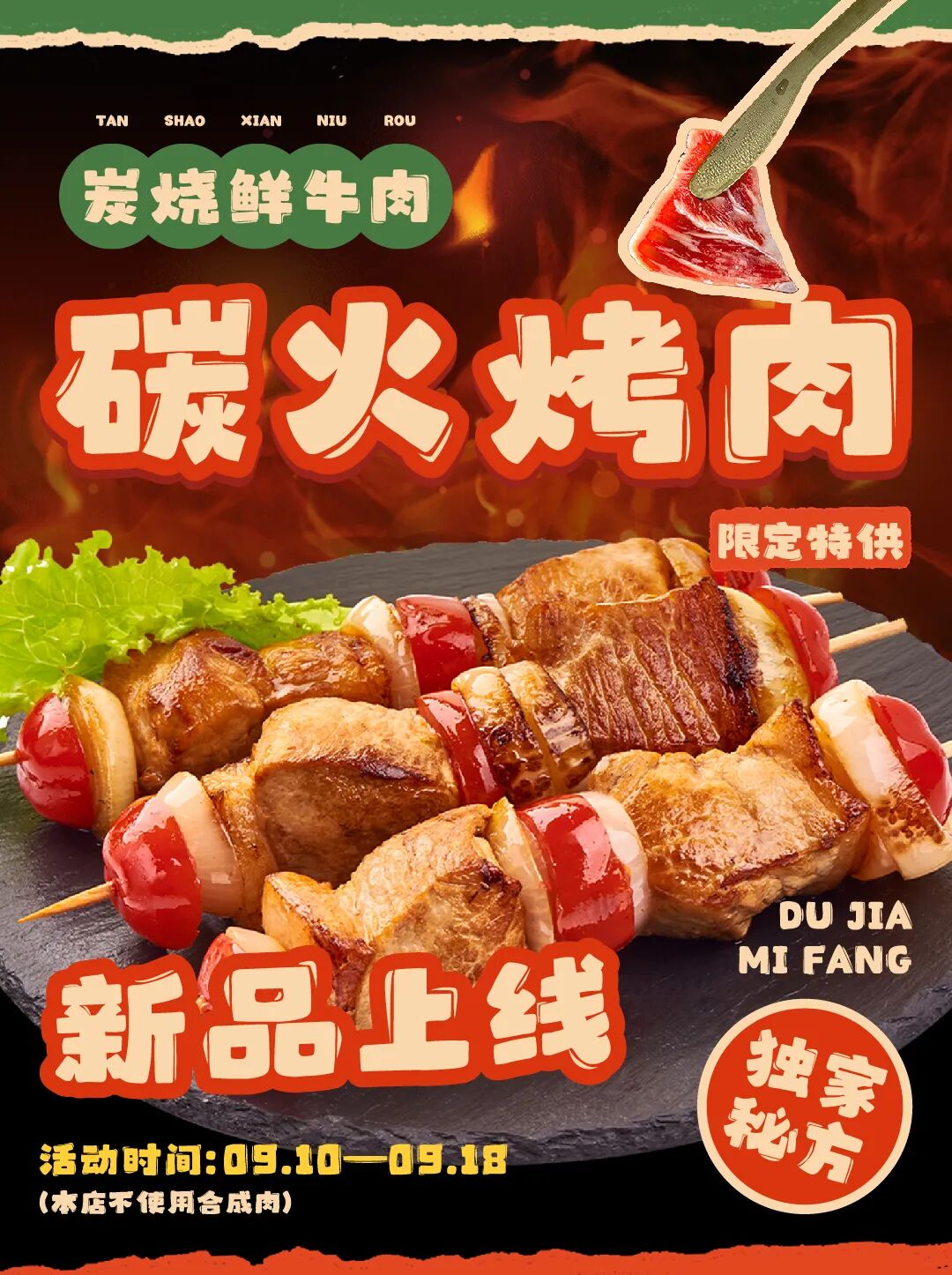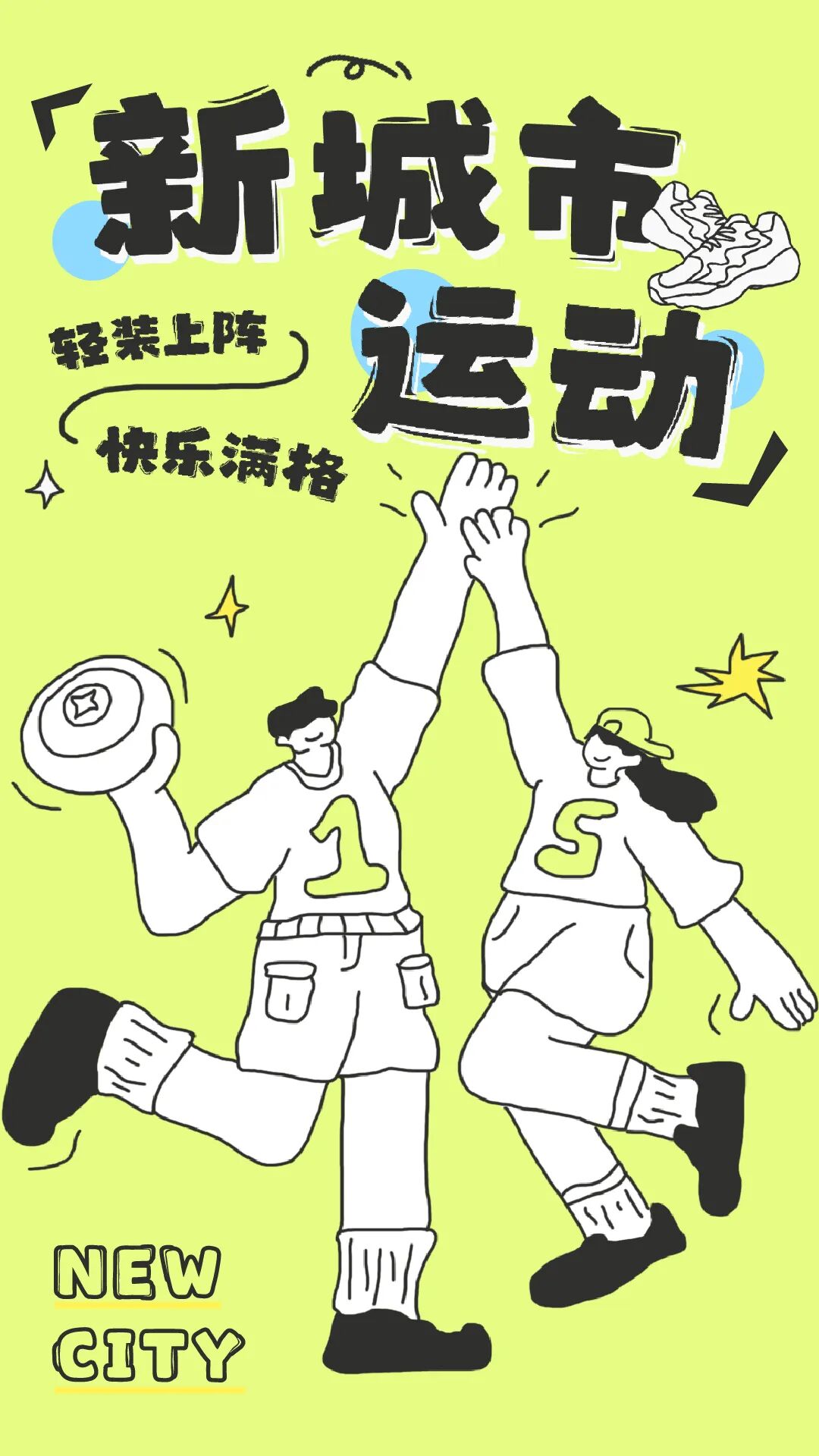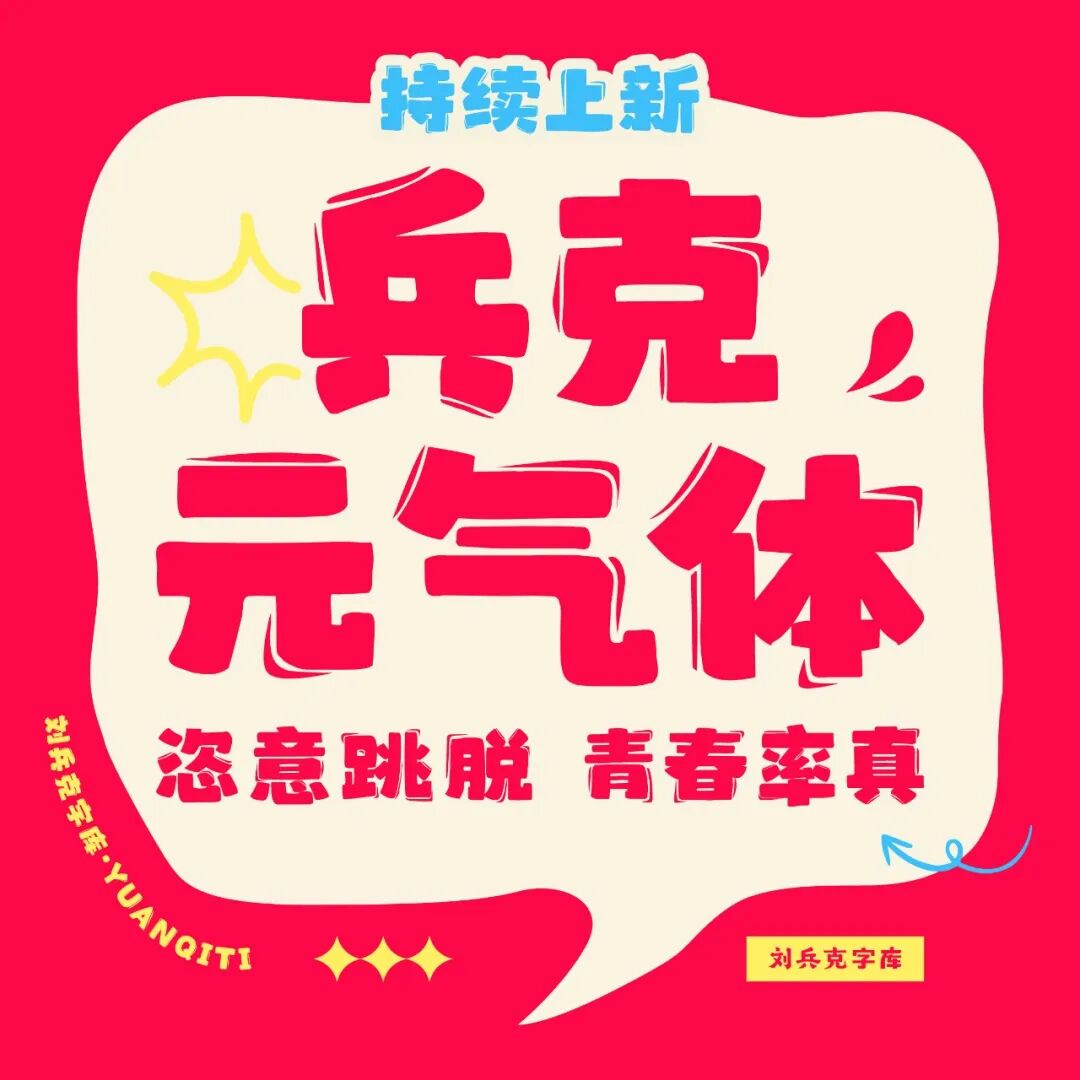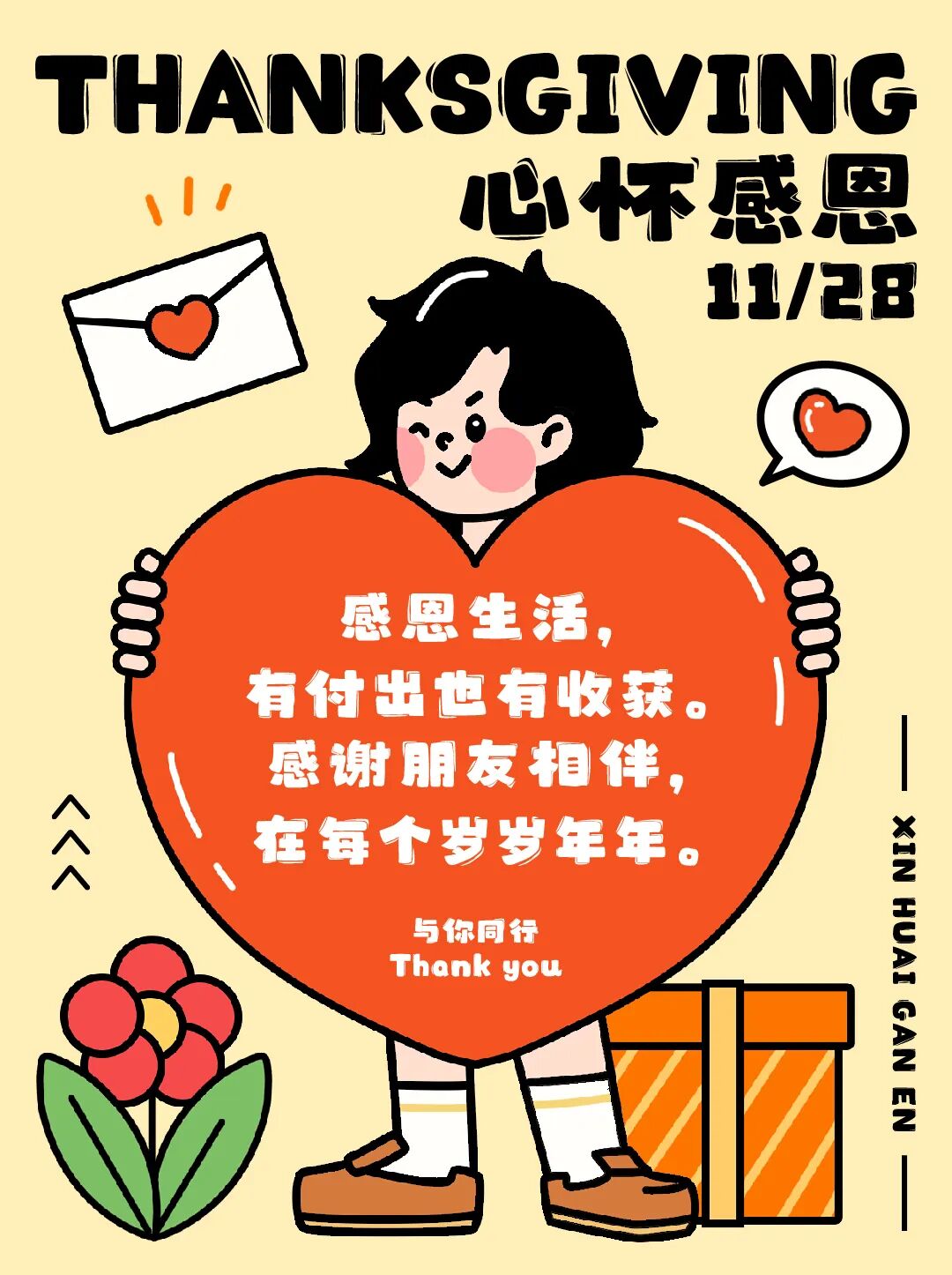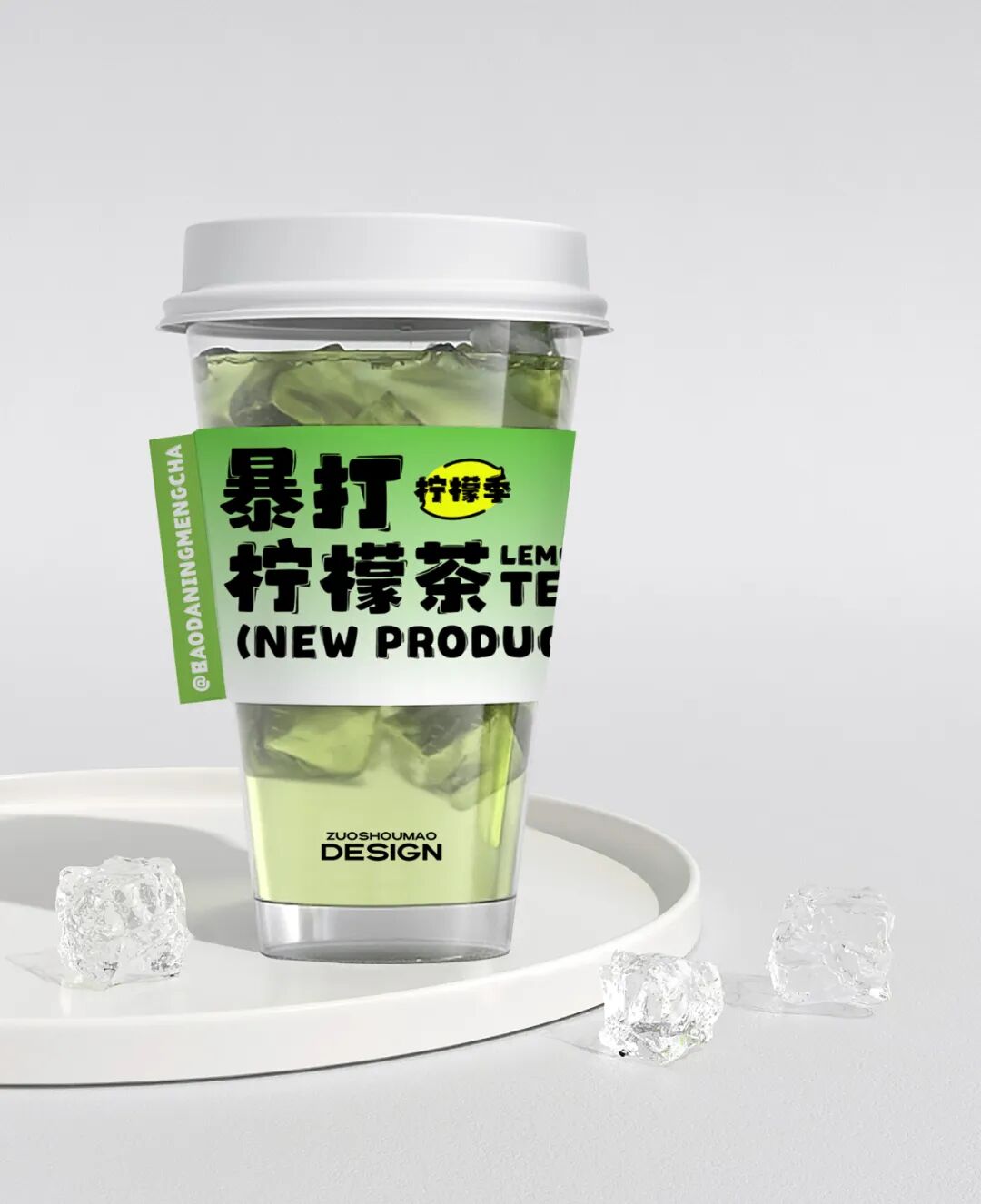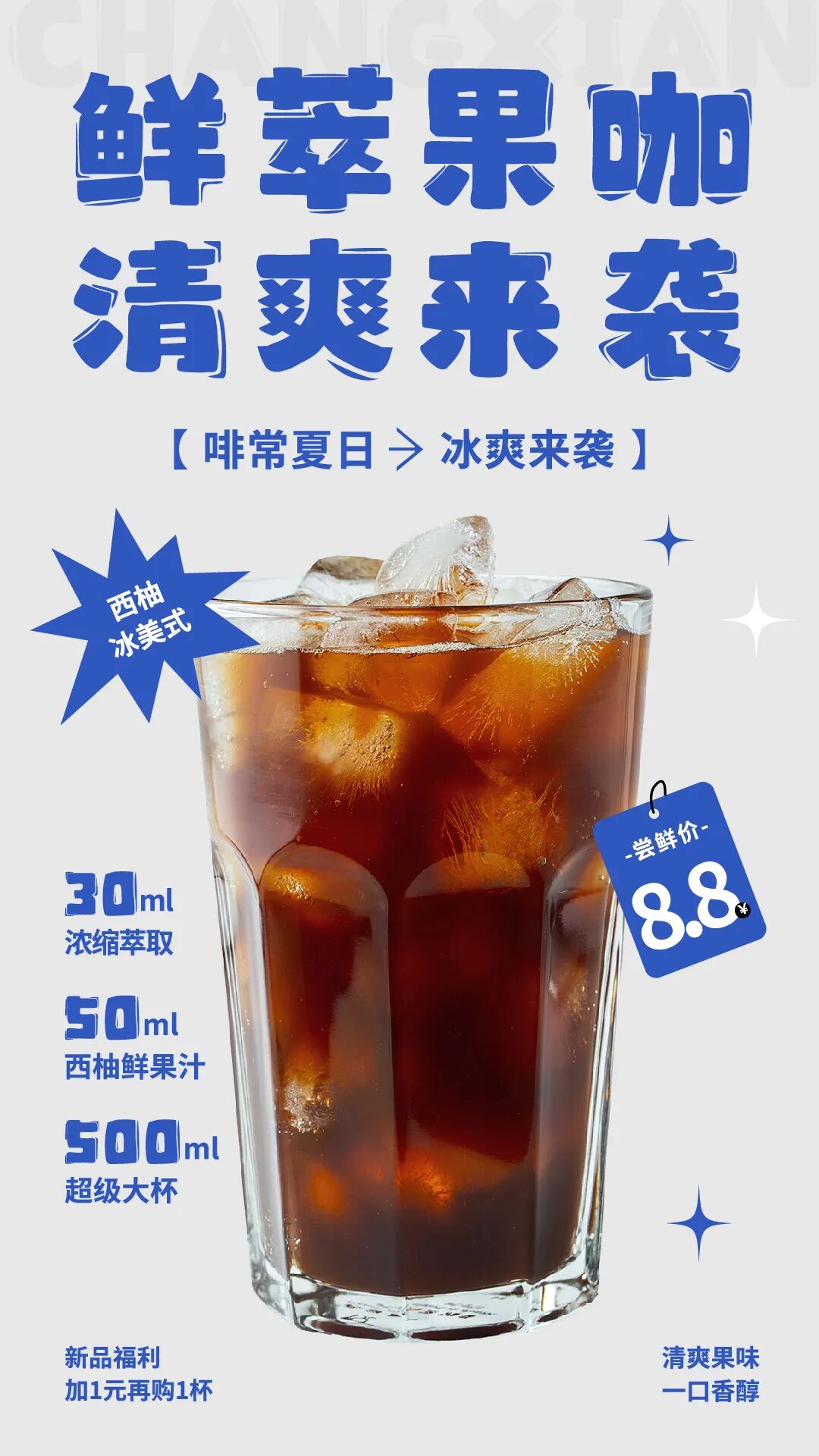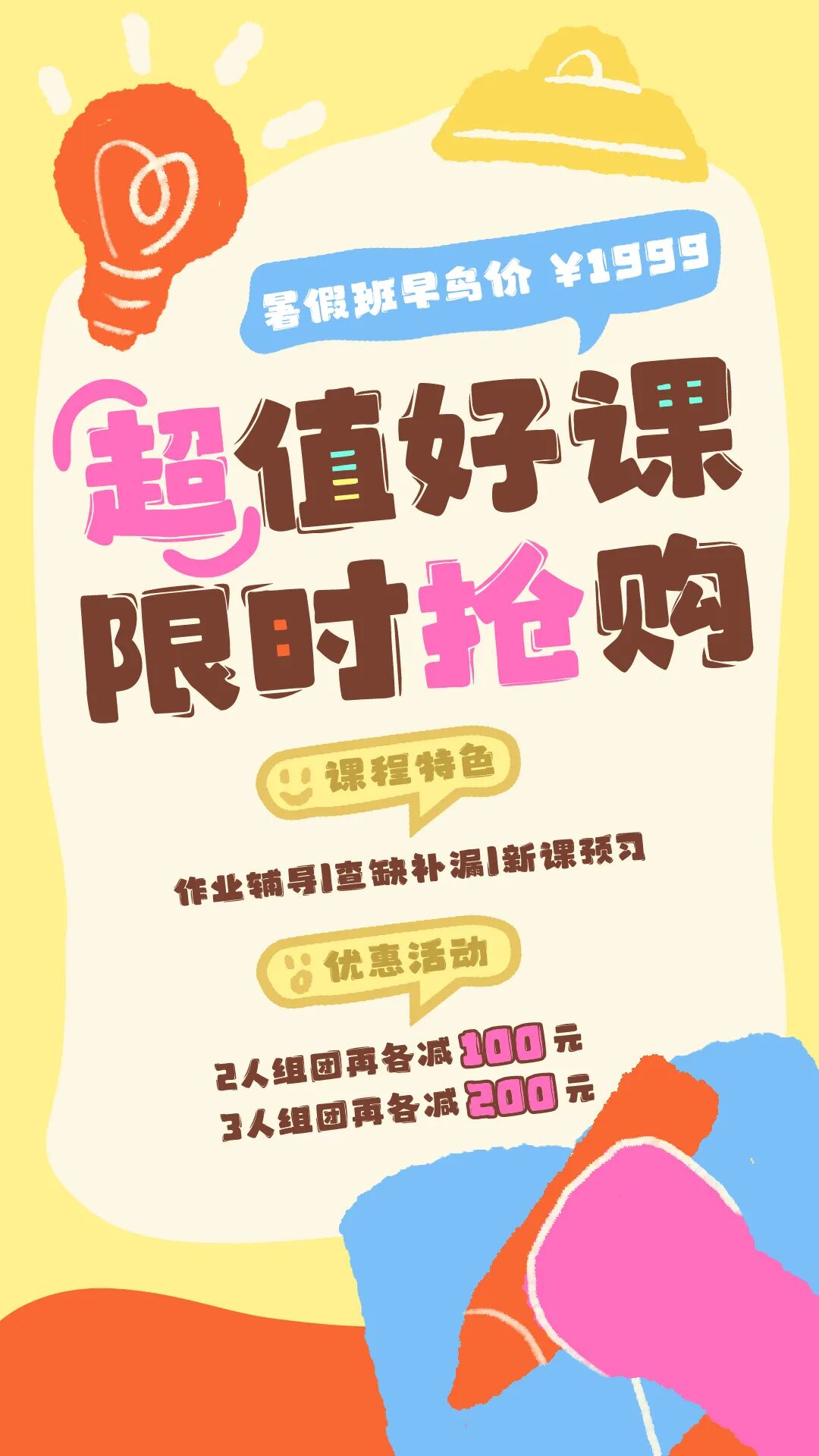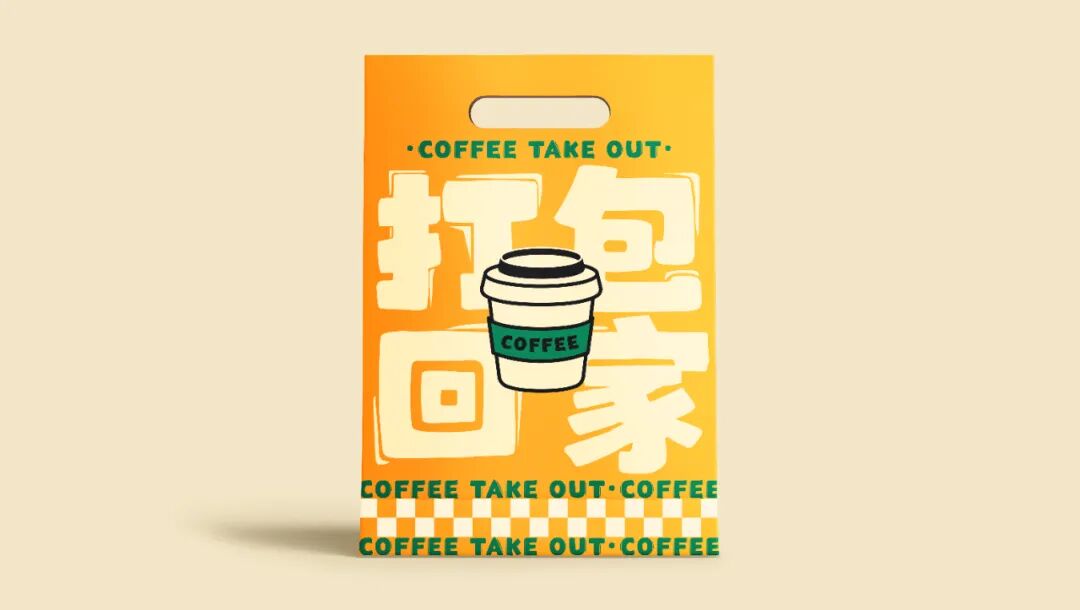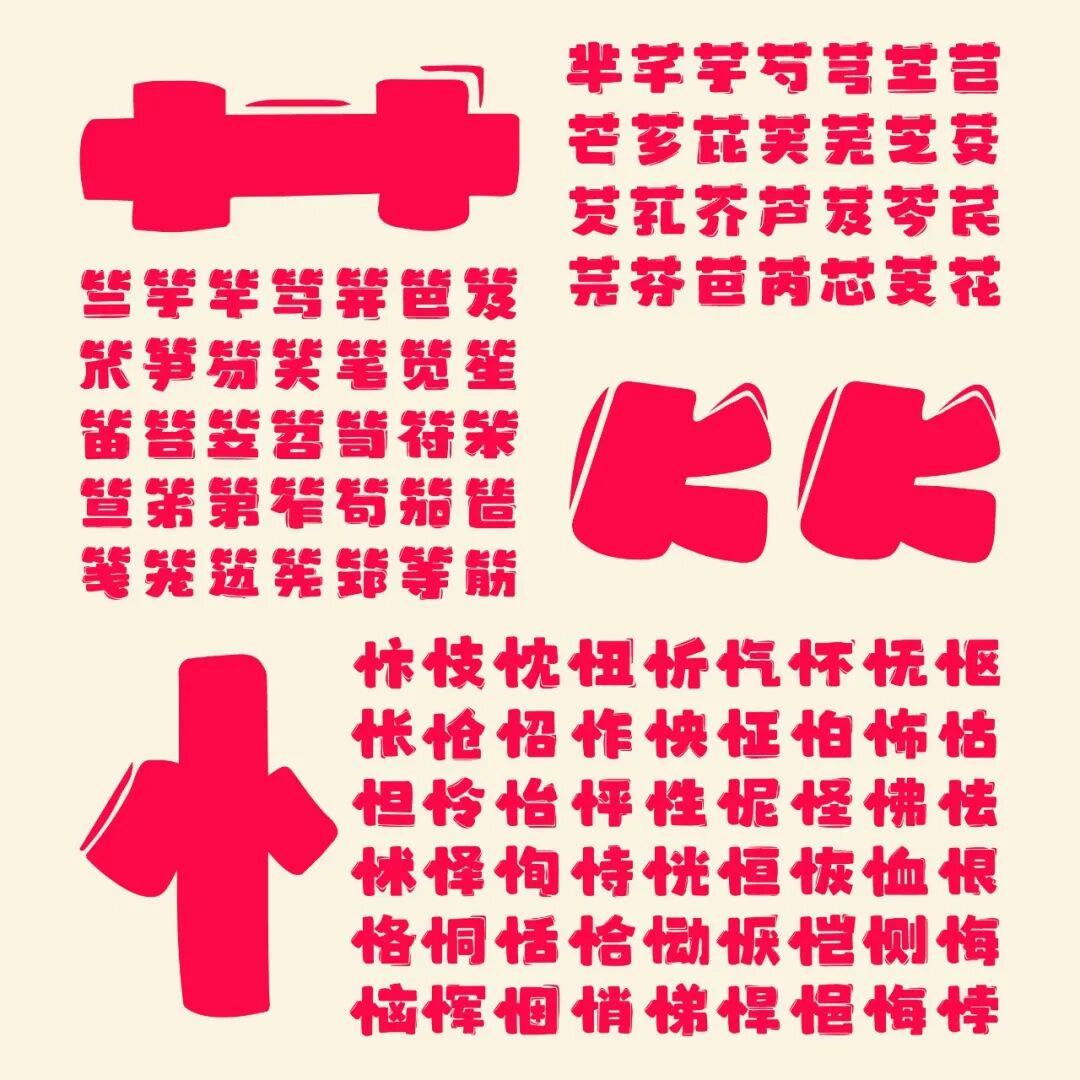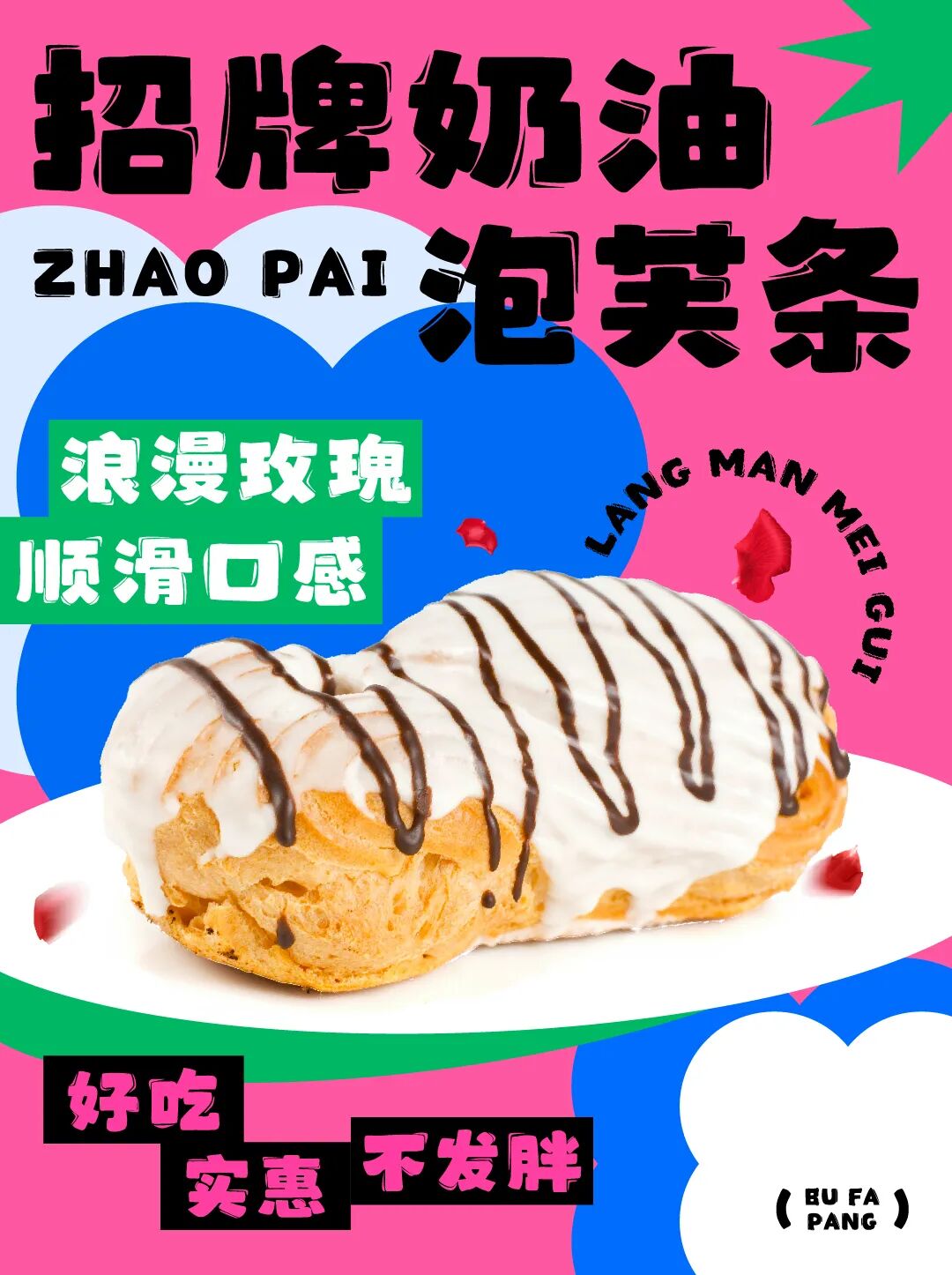
兵克元气体
兵克元气体,兵克元气体,风格可爱俏皮、憨态可掬,元气感鲜明;字体周边环绕不规则手绘线条,营造出前后错落的空间感,线条的手绘质感强化了字体的随性与灵动,视觉更具活力;适用于年轻化品牌、文创产品和儿童用品相关设计、日常消费品类包装、活动宣传等场景,用元气风格增强宣传的亲和力与吸引力。
兵克元气体字体介绍